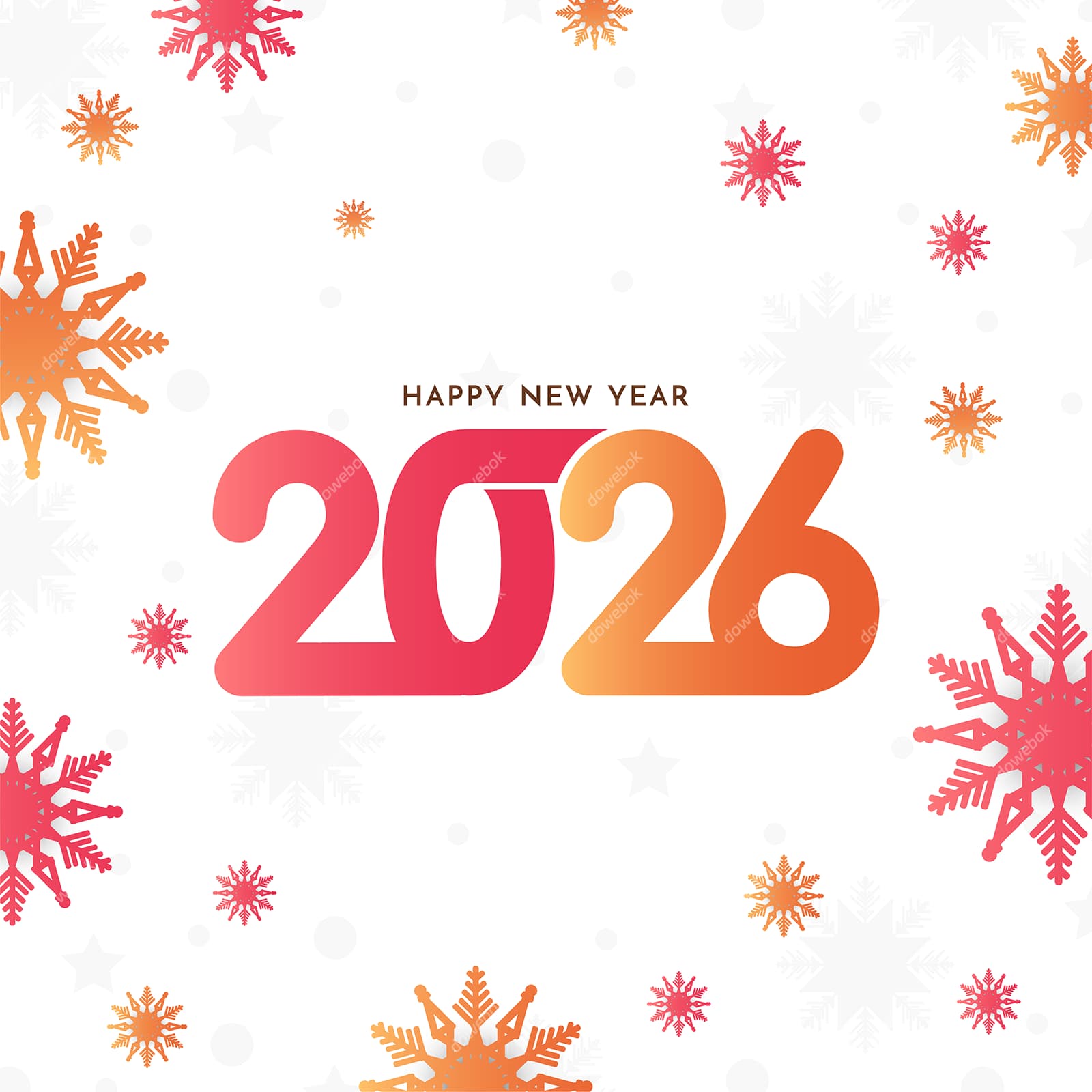
这是一款多彩雪花和数字设计的 2026 新年快乐矢量素材,纯白背景环绕着粉橙渐变的雪花装饰,营造出温暖的冬日氛围。“2026” 字体以粉橙渐变色呈现,柔和醒目,上方 “Happy New Year” 字样简约点缀。整体以暖调配色融合雪花元素,既显跨年的清新活泼,又用渐变色彩弱化冬日的清冷感,温馨中透出轻快的节日质感。